フォントワークスが無料で使える「SILオープンフォントライセンス」として、「Google Fonts」へのフォント提供を2021年1月15日から開始。無料で8書体をダウンロードしてフォント沼にハマろう!
フォントワークスは、2021年1月15日からは「SILオープンフォントライセンス」として自社のフォントをGoogle Fontsへ8書体の提供を開始した。
Google Fontsに提供した8書体は、手書き風の楷書系硬筆体「クレーRegular」「クレーSemiBold」、ディスプレイ書体の「ステッキ」、「ドットゴシック」、「トレイン One Regular(トレインはレイルウェイのGoogleFonts提供名称)」、「ランパート」、「レゲエ」、「ロックンロール」となる。
SILオープンフォントライセンスとして無料で使える「クレーRegular/SemiBold」
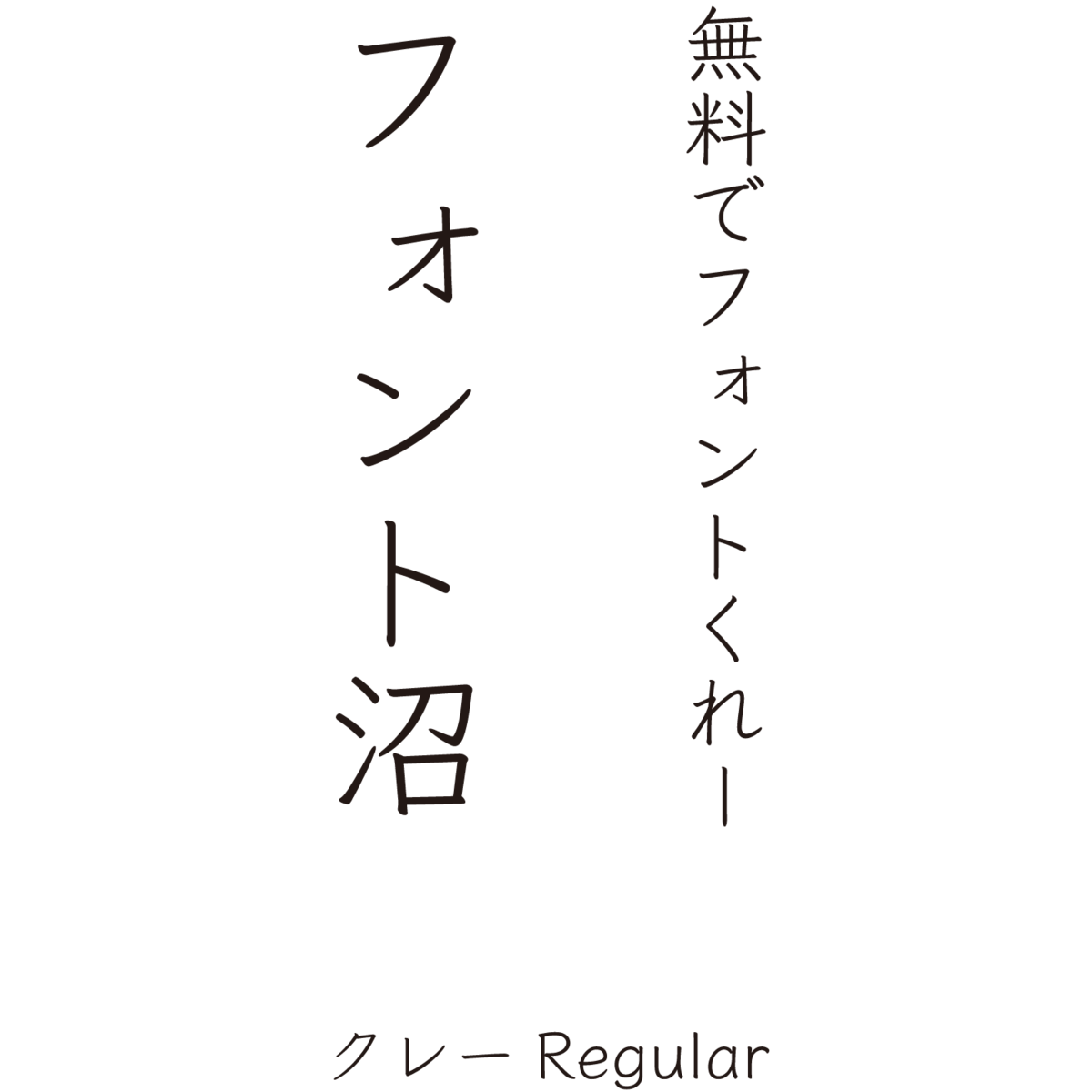
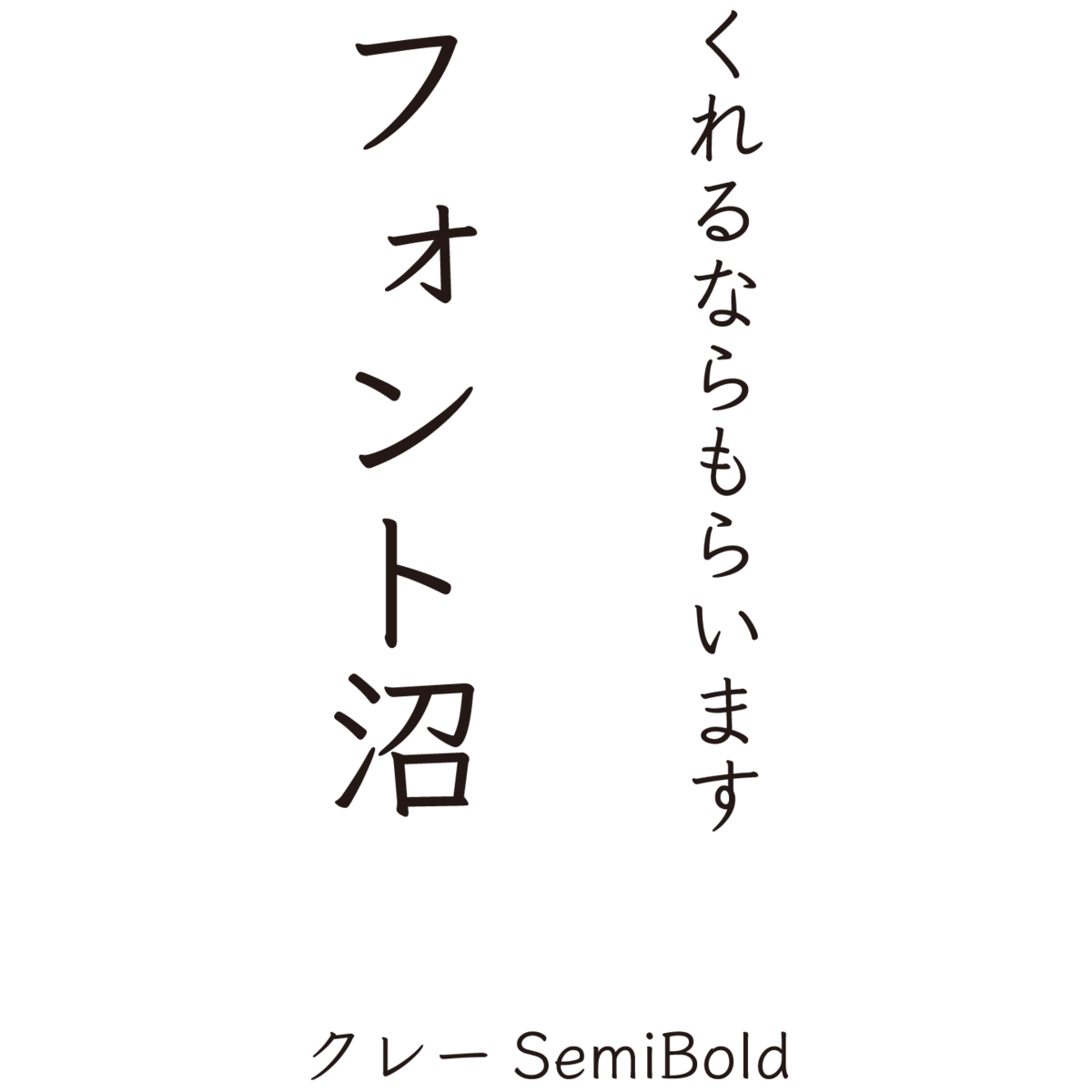
文字の起筆部と終筆部に硬筆の筆記具で書いた文字特有のアクセントをもたせた硬筆体。
毛筆の代わりに、鉛筆やペンなどを使って書いた手書き風の文字として独特の雰囲気が特徴で、楷書体や教科書体とは一味違う手書き風のイメージを持ち、本文組みに適した書体となる。
SILオープンフォントライセンスとして無料で使える「トレインRegular」
フォントワークスのゴシック体である「ロダン」をベースに二重の筆書き、もしくはアウトラインの内側と外側のラインで形成される書体。
インパクトはあるが、視覚的に威圧感を与えることのない快活でオープンなイメージを与えることができる。
また、トレインはレイルウェイのGoogleFonts提供名称でもある。
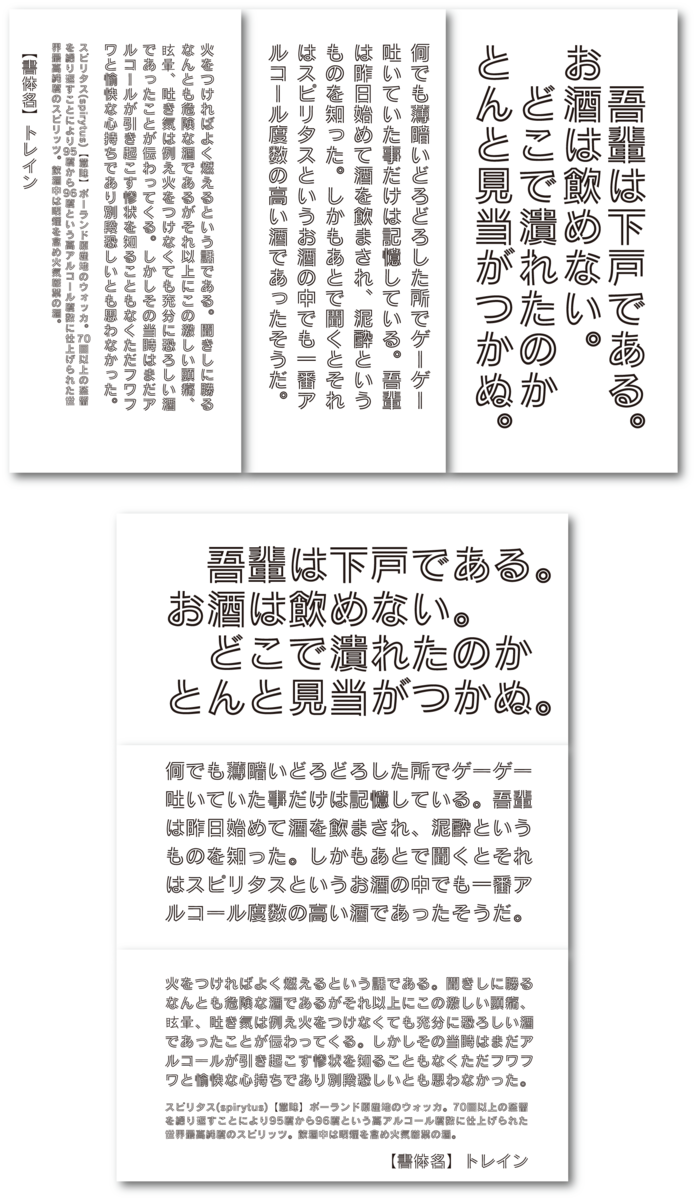
SILオープンフォントライセンスとして無料で使える「ロックンロールRegular」
フォントワークスのゴシック体である「ロダン」をベースにポップスタイルに仕上げたユニークな書体。生き生きと軽快で、躍動感のあるデザインが特徴。
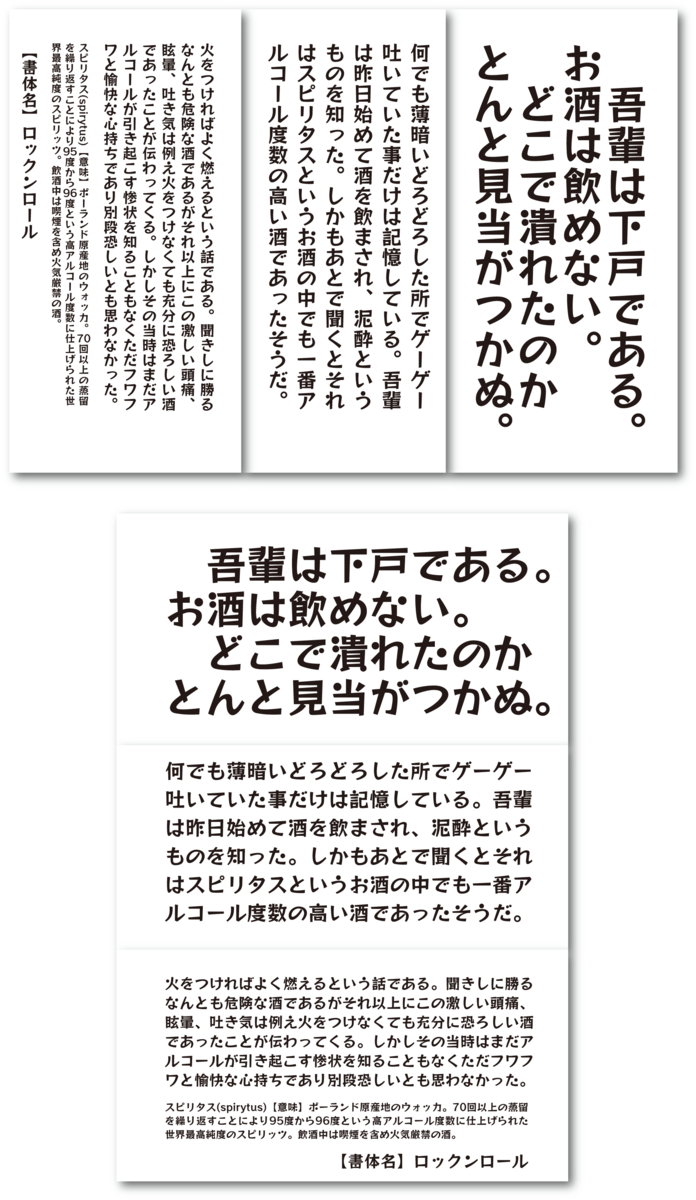
SILオープンフォントライセンスとして無料で使える「ステッキRegular」
ステッキ(棒)のように直線で表現されたデザインでありながら牧歌的な雰囲気をもつ素敵な書体。
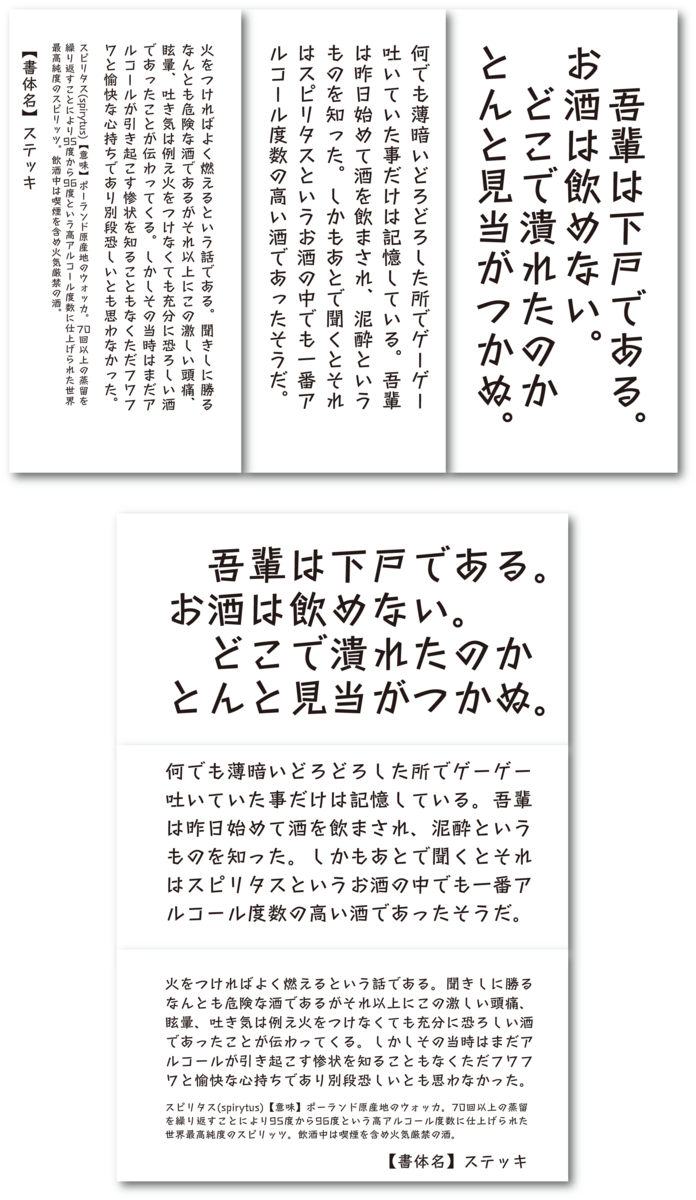
SILオープンフォントライセンスとして無料で使える「ランパートRegular」
フォントワークスのゴシック体である「ロダン」をベースに“ブロック”をイメージしたデザインで、立体的な壁のような感じを与えるユニークでオリジナルあふれるアウトラインシャドウ書体。力強さや頼もしさ、安定を表現したい場合にオススメ。
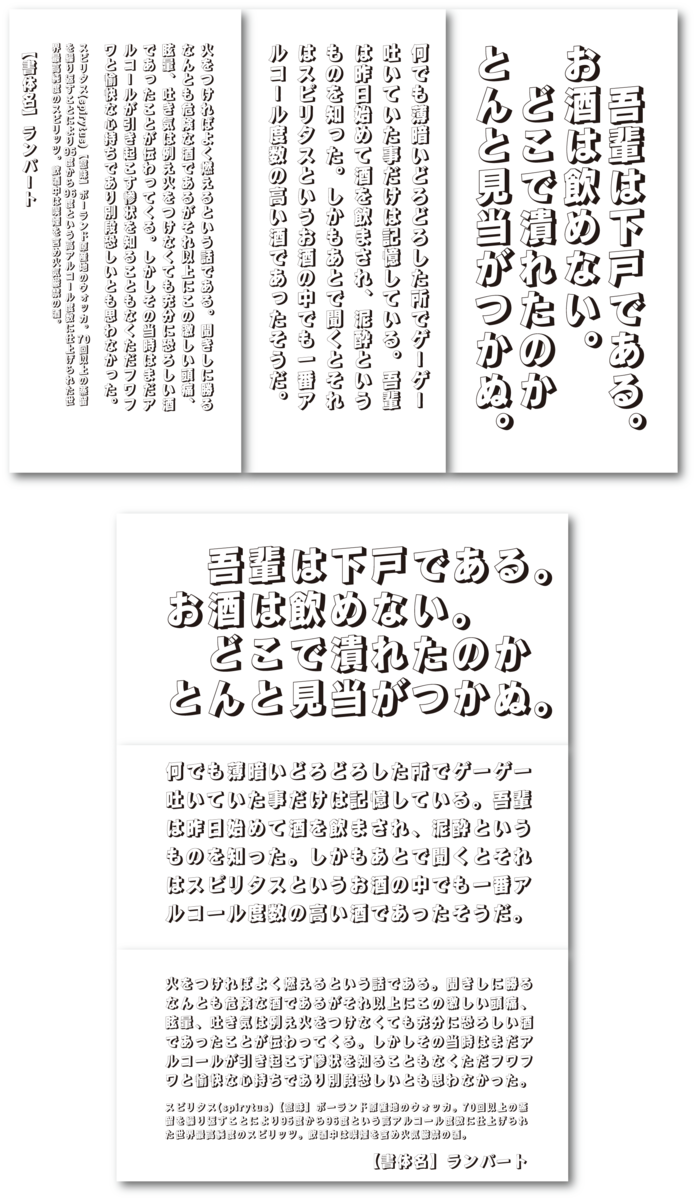
SILオープンフォントライセンスとして無料で使える「レゲエRegular」
フォントワークスのゴシック体です「ロダン」をベースに線の末端部分を細くデザインすることで、ダイナミックな鼓動感を出した書体。リズムや動き、活気を表現する場合にオススメ。
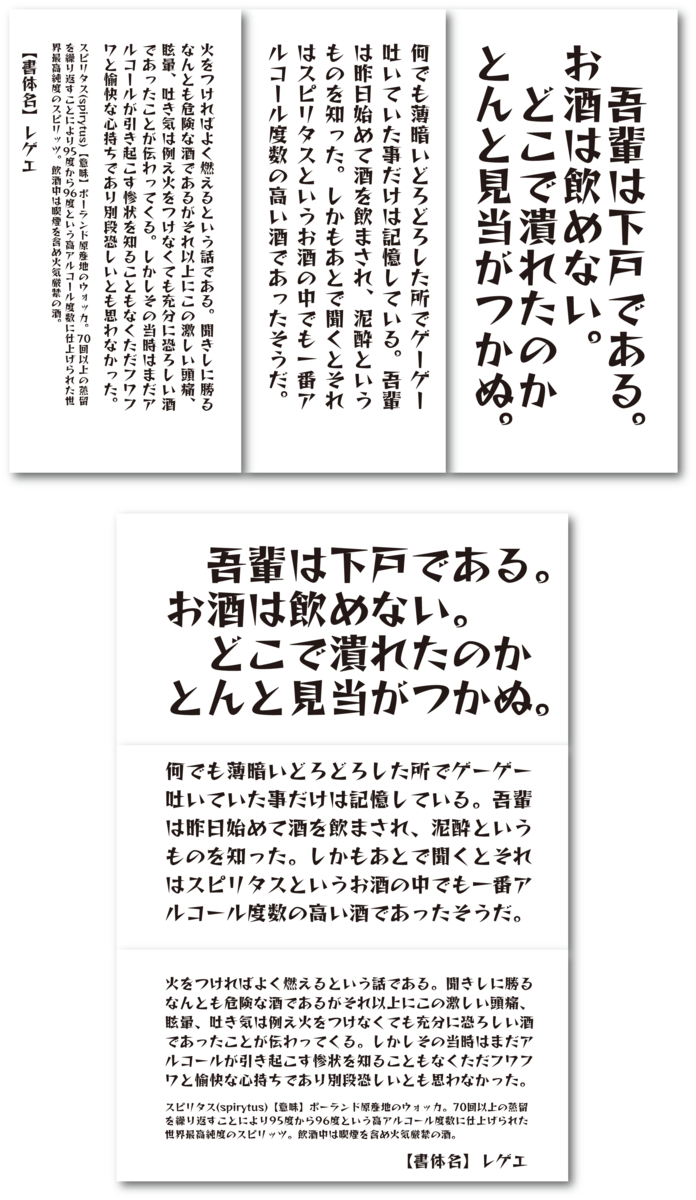
SILオープンフォントライセンスとして無料で使える「ドットゴシック16Regular」
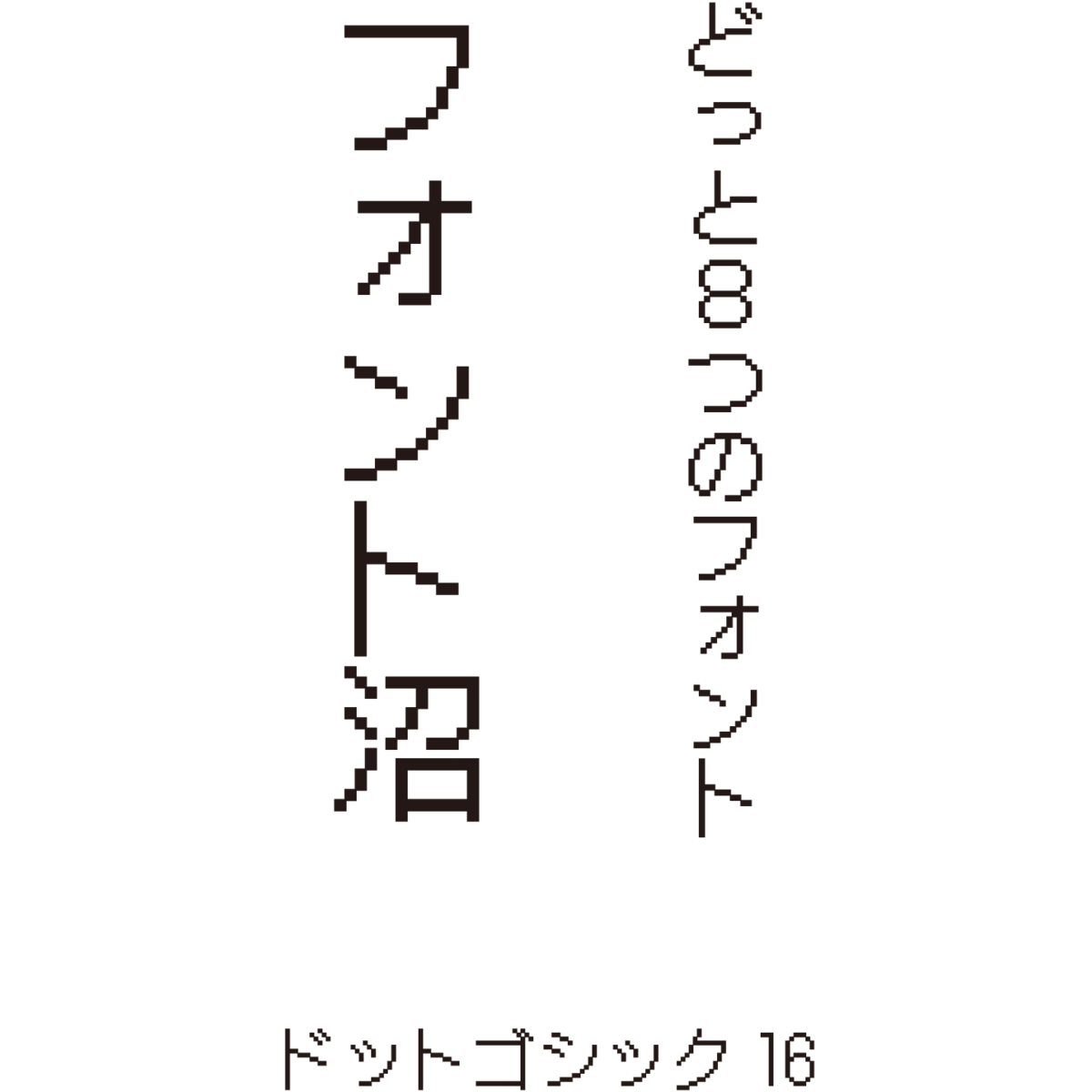
携帯の画面やパソコン画面の雰囲気を、そのまま印刷物などで表現したいというユーザーからの要望に応え、16×16のゴシック体のビットマップをベースに開発された書体。